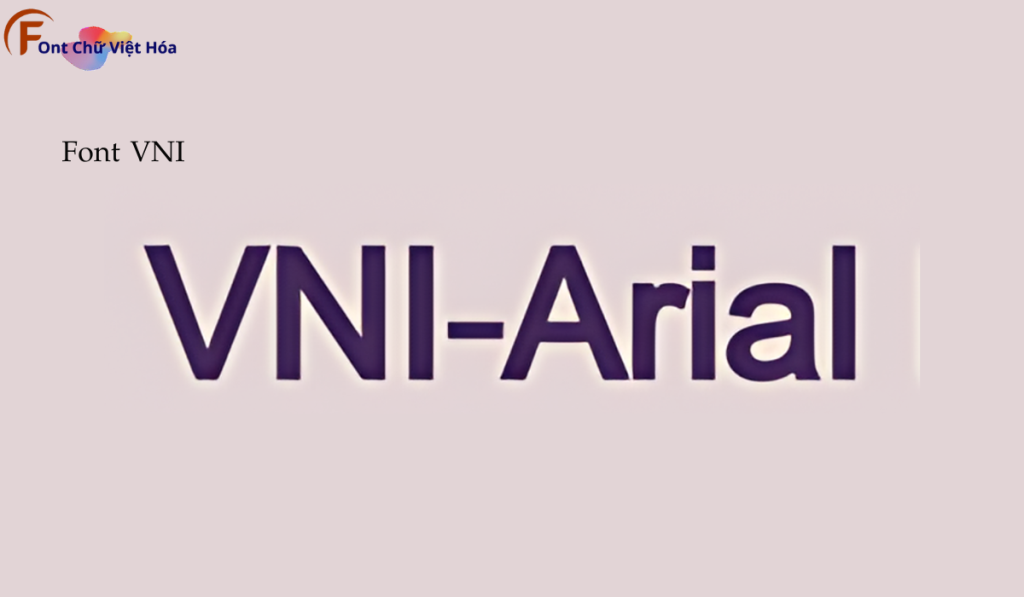
Font VNI Arial Việt Hóa
Kiểu chữ: Có chân
Độ dày: Regular, Bold, Italic, Bold Italic
Font VNI Arial Việt Hóa, thuộc bộ font VNI, mang phong cách sans-serif hiện đại và phổ biến, phù hợp cho các dự án thiết kế như tài liệu văn phòng, báo cáo, và bìa sách. Với các nét chữ không chân và độ dày đều đặn, Font VNI Arial Việt Hóa không chỉ dễ đọc mà còn tạo cảm giác chuyên nghiệp và gọn gàng. Việc Việt hóa font giúp người dùng dễ dàng tích hợp vào các thiết kế tiếng Việt, mang lại sự tiện lợi và nâng cao tính thẩm mỹ.